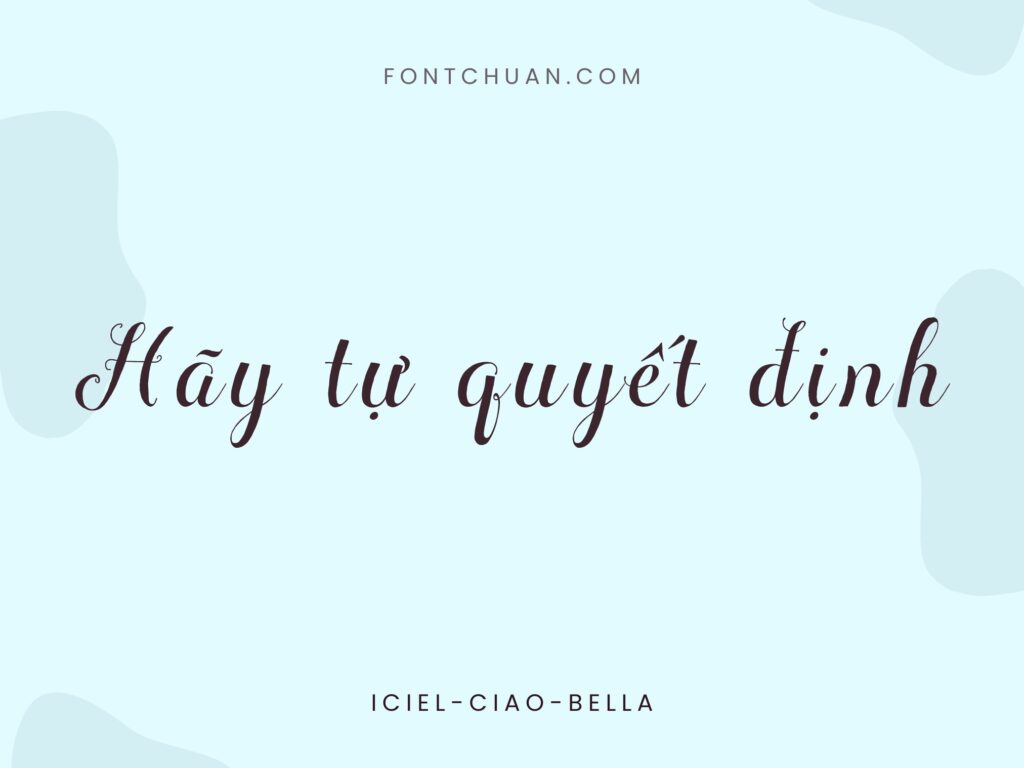
Font iCiel Ciao Bella Việt Hóa
Ciao Bella là một kiểu chữ viết tay tinh tế được thiết kế bởi Cindy Kinash và Charles Gibbons, phát hành vào năm 2014. Font này mang phong cách lãng mạn và thanh lịch, với các ký tự nghiêng mềm mại, tạo cảm giác gần gũi và thân thiện. Đặc biệt, Ciao Bella đã được Việt hóa bởi Iciel, hỗ trợ tiếng Việt cùng nhiều ngôn ngữ khác, đáp ứng nhu cầu đa dạng của người dùng. Thành viên của Font Chuẩn đã sưu tầm và chia sẻ font này, giúp cộng đồng thiết kế ứng dụng dễ dàng trong các dự án của mình.
Về đặc điểm thiết kế, Ciao Bella sở hữu các ký tự viết tay độc đáo, với đường nét uyển chuyển và tinh tế. Font này phù hợp cho các thiết kế như thiệp mời, logo, bao bì sản phẩm, và các ấn phẩm truyền thông xã hội. Ngoài ra, Ciao Bella còn thích hợp cho các ngành nghề như ẩm thực, quảng cáo, thiệp cưới và spa, cùng các sự kiện đặc biệt như lễ hội, sinh nhật, Valentine và Trung thu.